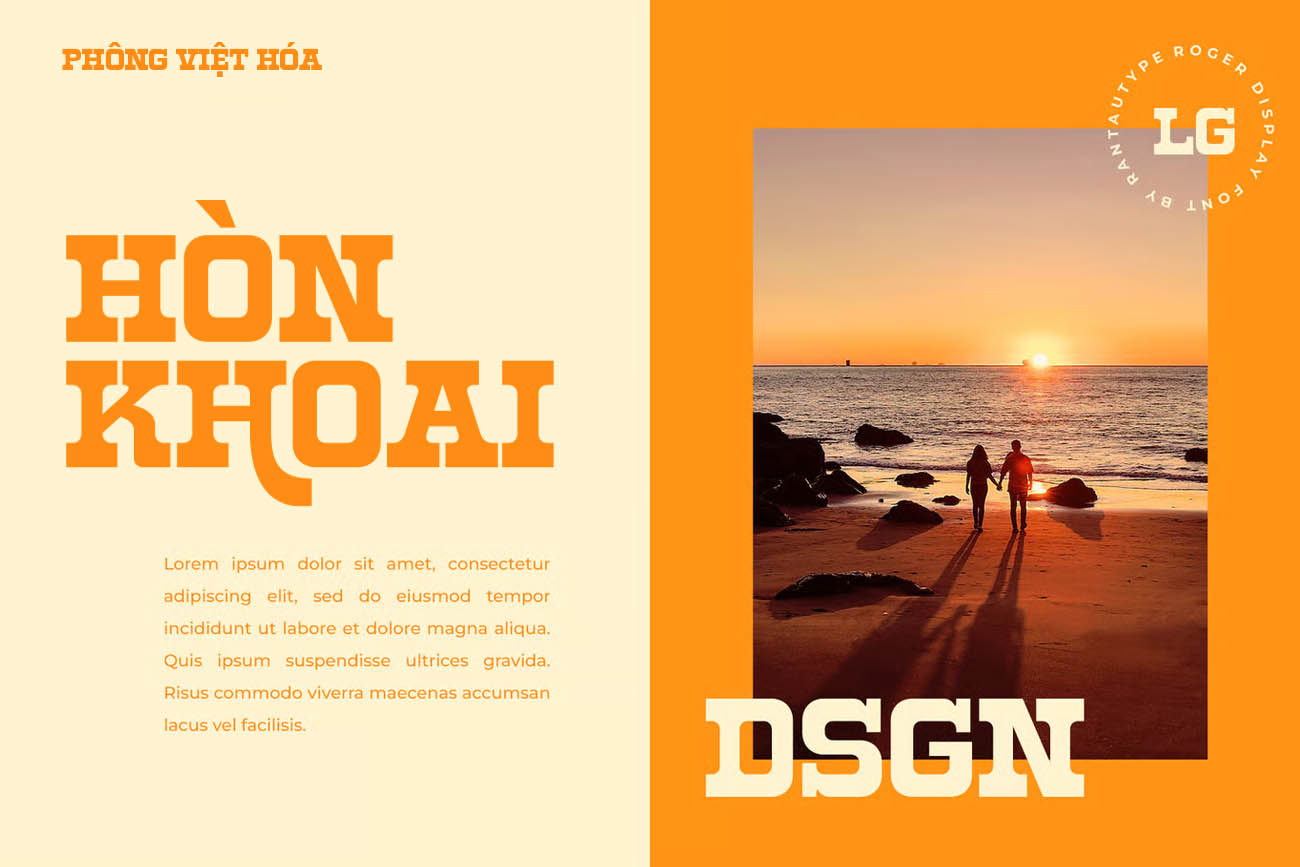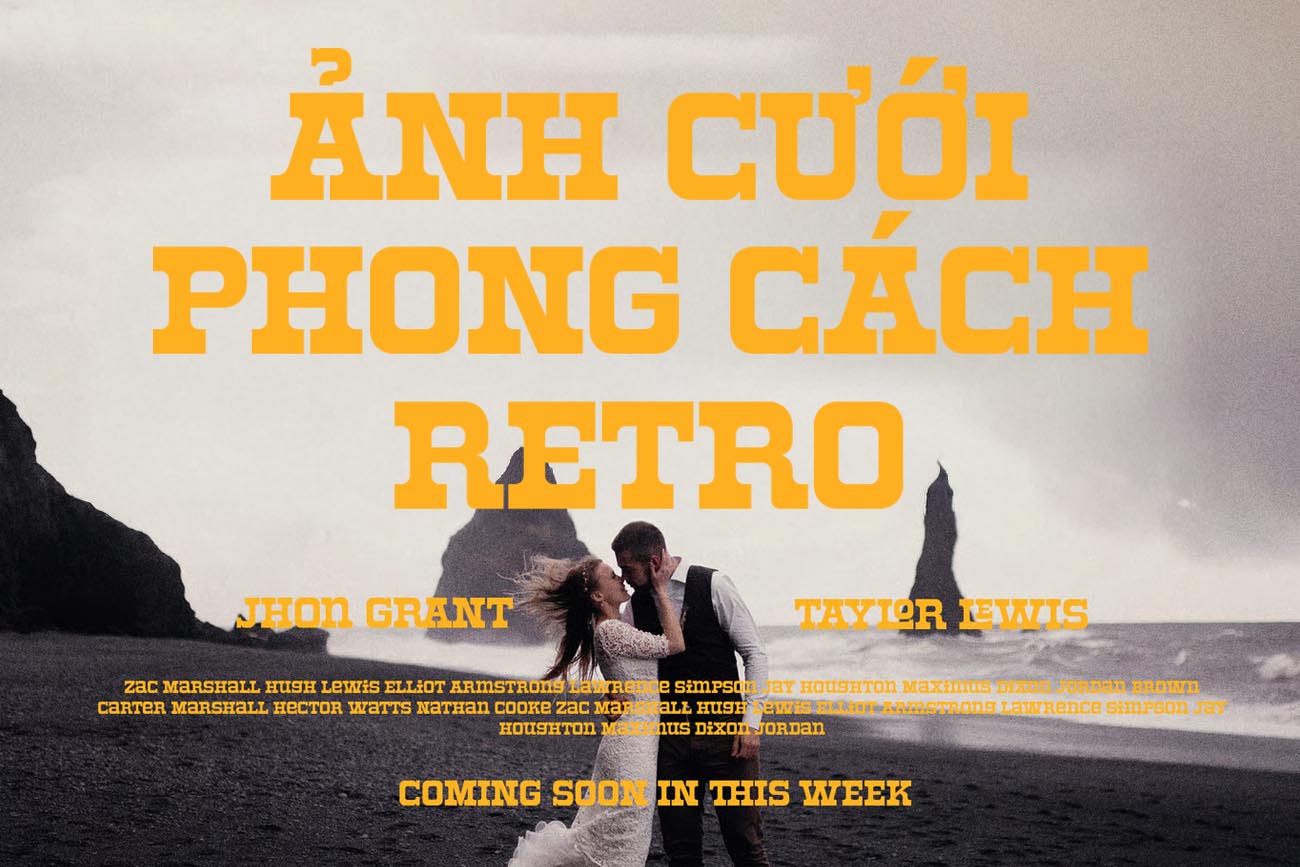
Font chữ Display đậm chất Retro TH Roge Việt hóa
Trong thế giới thiết kế đồ họa, xu hướng tìm về những giá trị hoài cổ chưa bao giờ hạ nhiệt. Hôm nay, chúng tôi xin giới thiệu đến cộng đồng Designer bộ phông chữ TH Roger – một phiên bản Việt hóa hoàn hảo từ tác phẩm gốc đình đám của Rantau Studio. Đây là sự lựa chọn lý tưởng nếu bạn đang tìm kiếm một font chữ Display độc đáo để tạo điểm nhấn thị giác mạnh mẽ cho các dự án sáng tạo của mình.
Vẻ đẹp hoài cổ đầy lôi cuốn của TH Roger
TH Roger (nguyên bản là Roger) được thiết kế dựa trên cảm hứng từ những thập niên cũ, mang trong mình linh hồn của phong cách Retro và Groovy. Với những đường nét dày dặn, các đường cong uyển chuyển và sự phá cách trong cấu trúc ký tự, bộ font này tái hiện xuất sắc vẻ đẹp của dòng font chữ cổ điển.
Không giống như các phông chữ văn bản thông thường, TH Roger sinh ra là để tỏa sáng ở kích thước lớn. Tính chất của một font chữ Display giúp nó trở nên nổi bật trên các thiết kế tiêu đề (headline), logo thương hiệu, bao bì sản phẩm, bìa tạp chí hay các tấm poster sự kiện mang phong cách vintage. Sự hiện diện của TH Roger trong bản thiết kế sẽ ngay lập tức thu hút ánh nhìn và gợi lên cảm giác thân thuộc, ấm áp nhưng cũng đầy cá tính.
Mặc dù bản gốc từ Rantau Studio đã rất xuất sắc, nhưng rào cản lớn nhất đối với Designer Việt chính là hệ thống dấu câu. Hiểu được nhu cầu đó, đội ngũ TH đã thực hiện Việt hóa chi tiết bộ font này.
Phiên bản TH Roger không chỉ đơn thuần là thêm dấu. Các dấu tiếng Việt được thiết kế tỉ mỉ để hòa hợp với tổng thể phong cách font chữ cổ điển vốn có, đảm bảo không làm phá vỡ cấu trúc thẩm mỹ của từng ký tự. Bên cạnh đó, các vấn đề về khoảng cách (kerning) khi gõ tiếng Việt cũng đã được tinh chỉnh, giúp dòng chữ luôn liền mạch và cân đối.